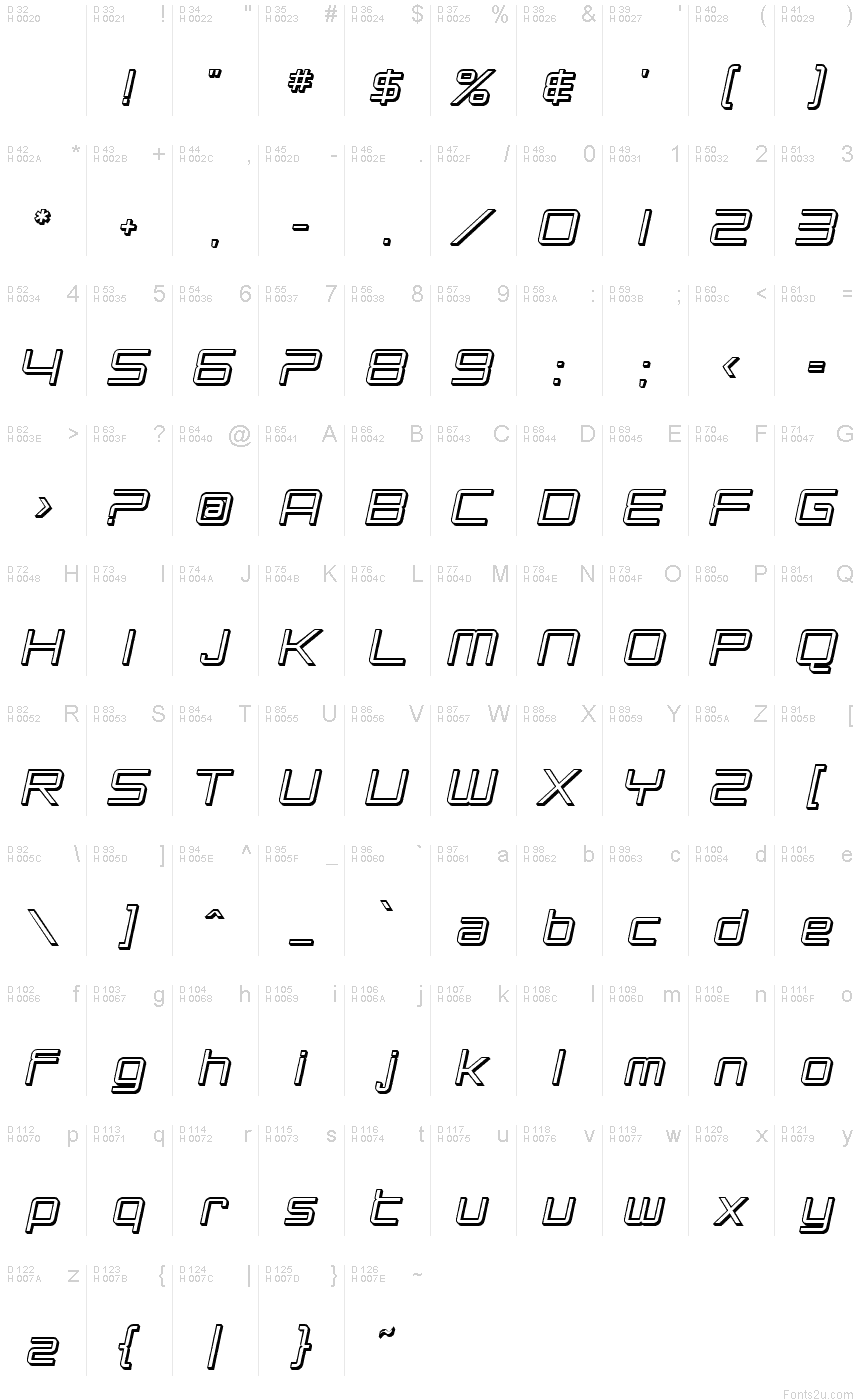
SF Chromium 24 Oblique من ShyFoundry هو خط عرض مجاني بمظهر مستقبلي، مستوحى من جماليات الخيال العلمي في عصر الكروم. تميل الحروف إلى الأمام بضربات طويلة وناعمة وزوايا مقصوصة، مما يمزج بين الهندسة المربعة والمنحنيات المستديرة ليمنح الخط طابعاً سريعاً واصطناعياً مع لمسة ريترو تذكرنا بتكنولوجيا أواخر التسعينيات.
يعمل هذا الخط بشكل ممتاز في شعارات الألعاب، ومنشورات الموسيقى الإلكترونية، وبطاقات العناوين، وعناوين الملصقات، وأغلفة المجلات حيث تحتاج إلى خط مجاني يوحي بالحركة دون أن يبدو فوضوياً. وبفضل الخطوط الخارجية المفتوحة والأشكال الممتدة بميل ثابت للأمام، فهو مناسب أيضاً للعلامات التجارية القصيرة، وملصقات الواجهات، والشعارات النصية المدمجة التي تبحث عن طابع ميكانيكي حاد.